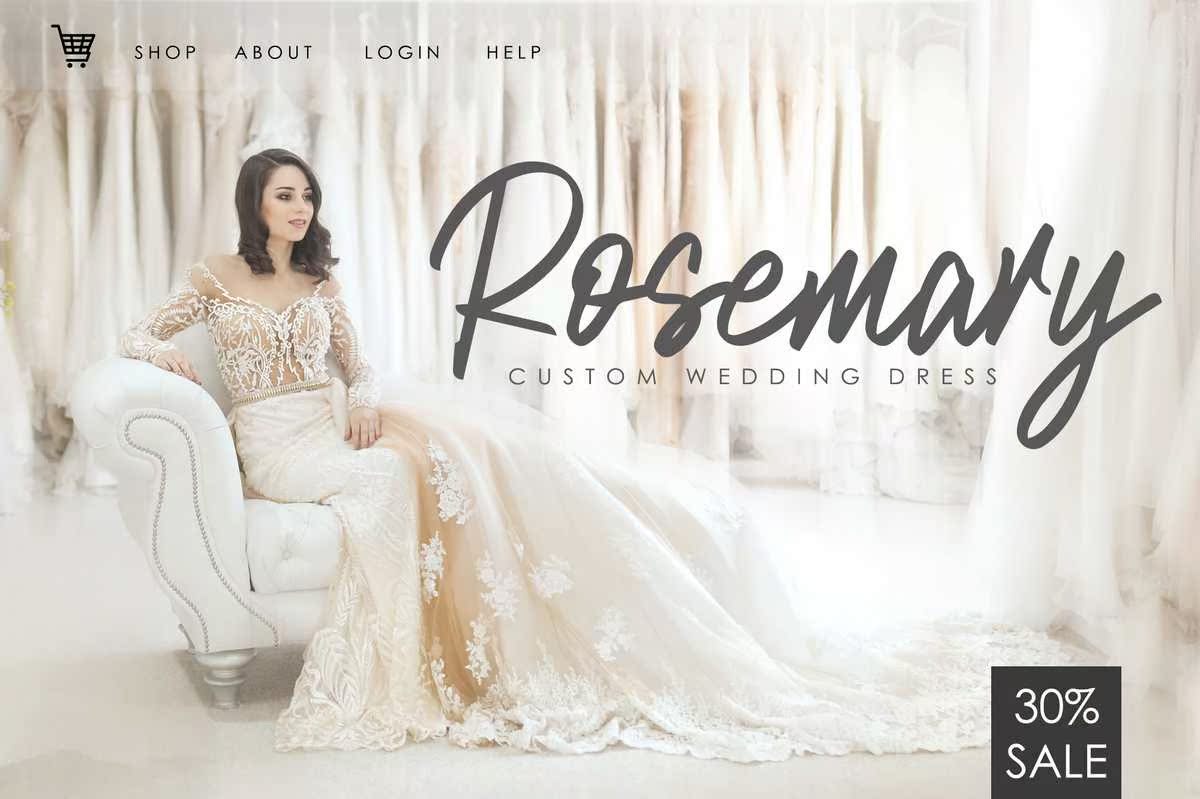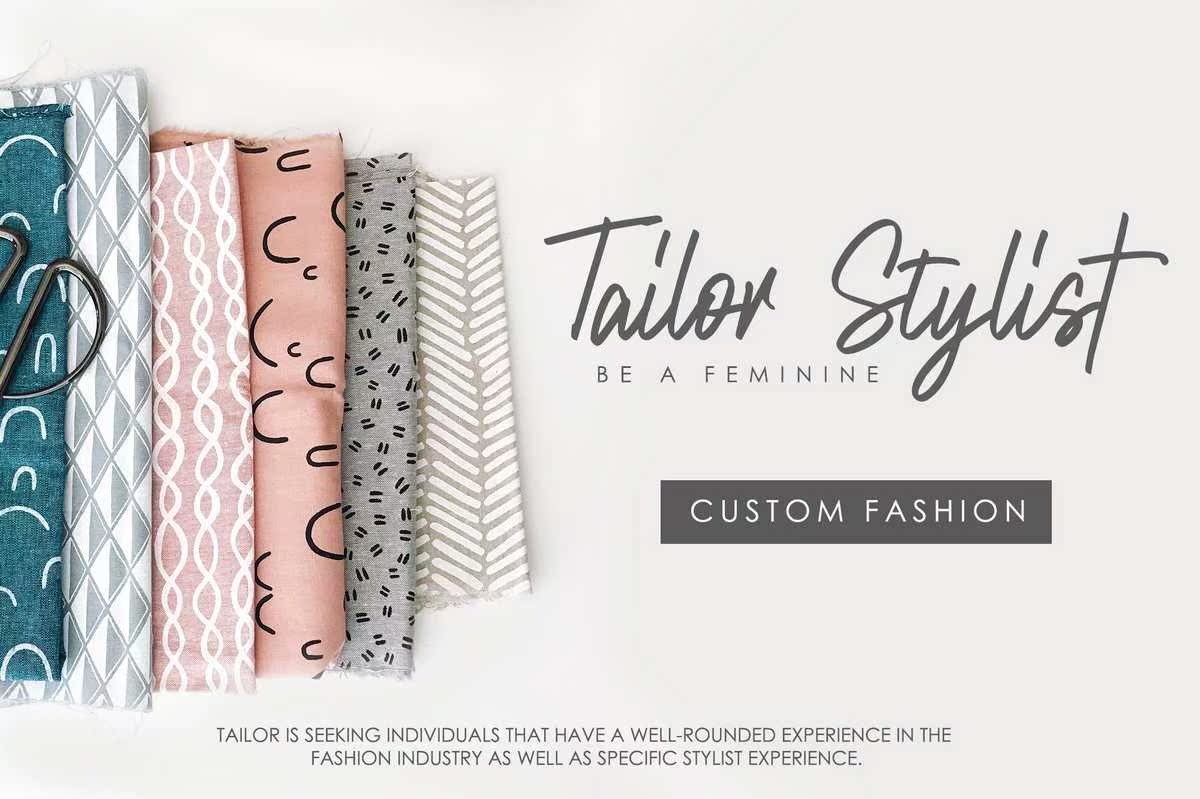
RunSell Studio介绍了一种专门用于时尚的字体。此字体与一些设计中的应用程序相匹配,包括日志类型、杂志、头条博客或网站、包装、品牌、,和更多产品。此字体给人留下了美好的印象。NataliaRosaline将为您提供更新的功能和其他感兴趣的字体。此字体将始终用于设计您所创建的产品。RunSell Studio介绍了一种专为时尚设计的字体。此字体与一些设计中的应用程序相匹配,如日志类型、杂志、头条博客或网站、包装、品牌、,和更多产品。此字体有一个漂亮的印象。NataliaRosaline将更新功能和其他感兴趣的字体,供您使用。此字体始终可以用于设计您创建的字体。